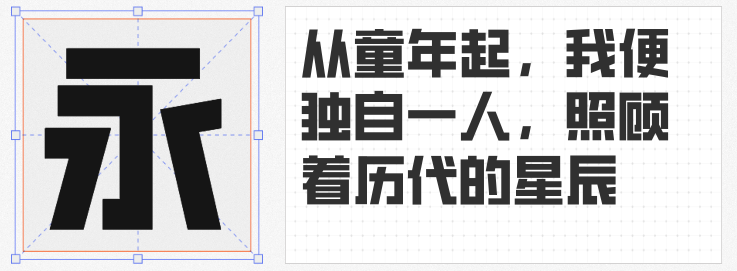
在视觉设计中,标题与核心信息的呈现往往需要极具冲击力的字体来强化视觉效果。特粗字体因其强烈的存在感和现代感,成为品牌海报、活动主视觉等场景的热门选择。本文精选四款免费可商用的特粗字体,兼顾设计感与实用性,助你轻松打造吸睛设计!
作为思源宋体的反向插值衍生字体,USMCC源简特粗体完美继承了思源系列的优雅骨架,同时通过加粗处理赋予其更强的视觉张力。其笔画粗细均匀,结构稳重,既能与思源其他字重(如Regular、Bold)和谐搭配,又能独立作为标题字体使用。尤其适合需要传递传统文化底蕴与现代力量感结合的设计场景,如文化展览海报、品牌宣言标语等。
基于热门字体得意黑改造的字魂扁桃体,以6°-8°的倾斜角度与挺拔高挑的字形为特色,在保留原字体时髦基因的同时,通过加粗字重与略微加宽字身,强化了视觉重量感。其标志性的「喇叭口」笔画末端设计,让字体仿佛自带「微笑弧度」,既充满活力又不失亲和力。适用于科技产品宣传、潮流品牌标语等需要年轻化表达的场景。
Aa厚底黑采用窄长字形与大弧度曲线设计,搭配超厚实的底部笔画,形成独特的「悬浮感」视觉效果。字体活泼而不失稳重,适合需要打破常规、传递轻松氛围的设计,如儿童品牌、创意市集海报或社交媒体趣味配图。
这款为抗击疫情创作的字体,以刚劲有力的笔画和简洁的几何结构传递坚定信念。特粗字重与方正字形结合,赋予其极强的视觉冲击力,适合公益宣传、社会议题海报或需要强调使命感的设计场景。